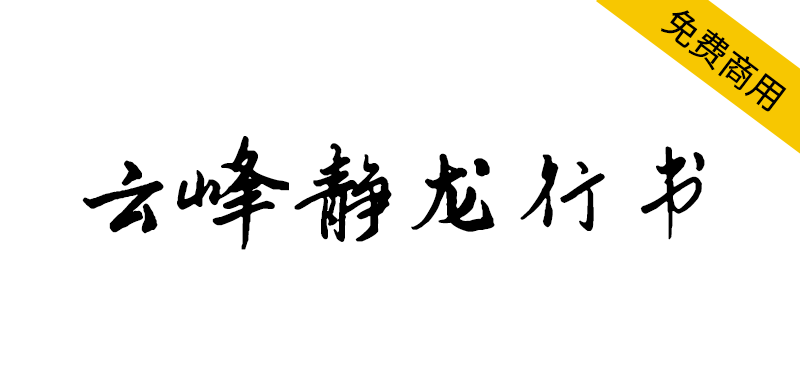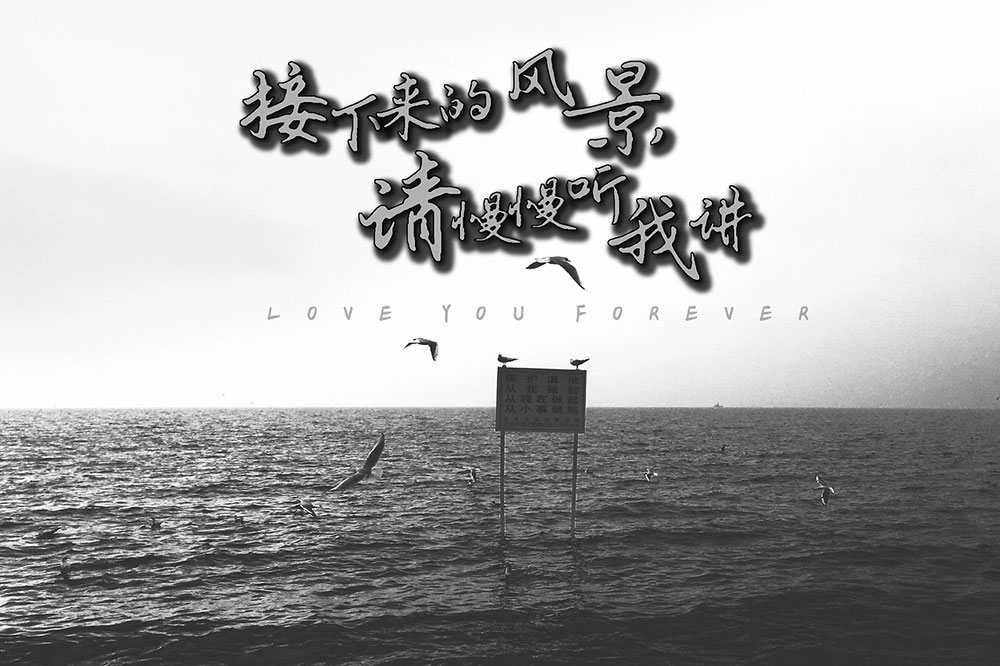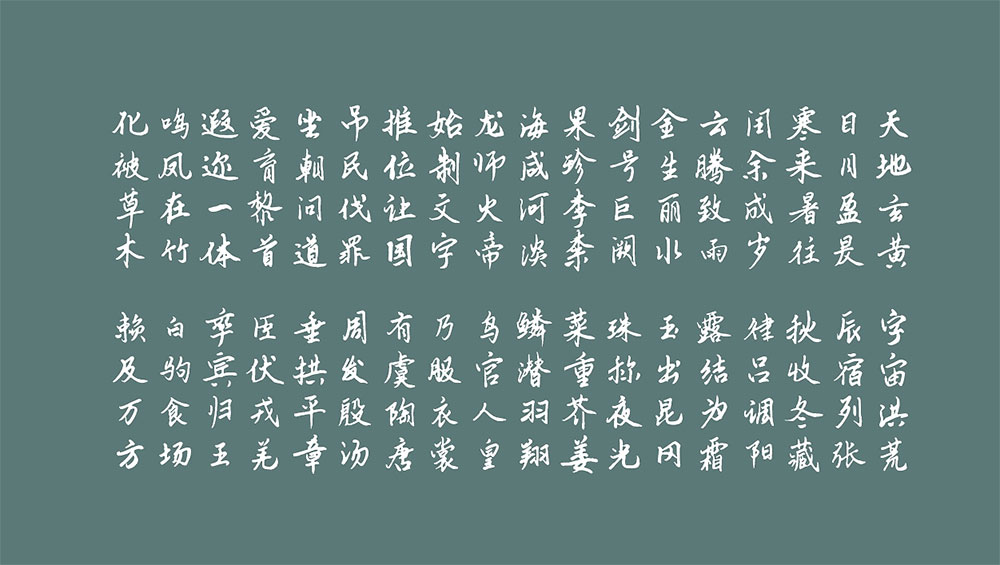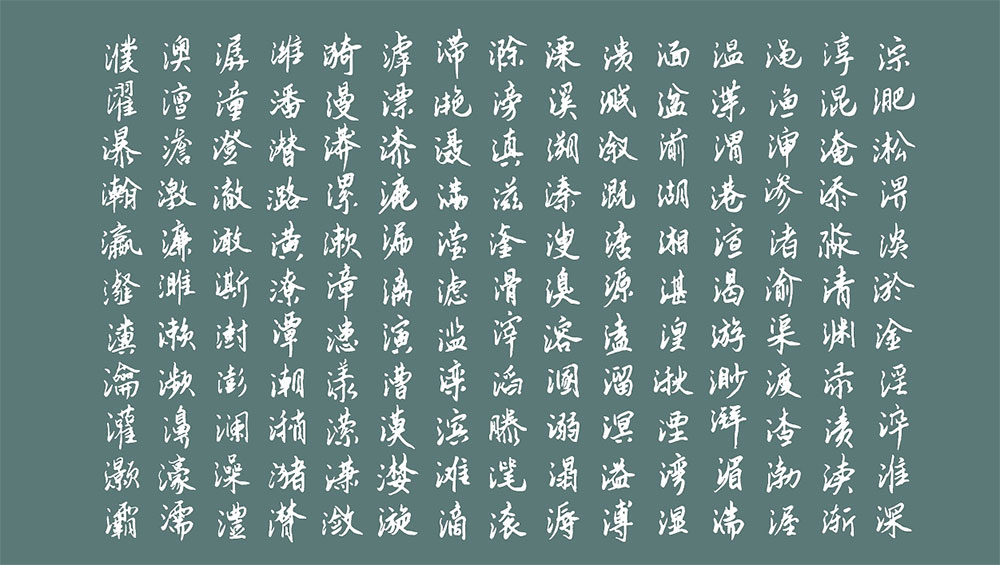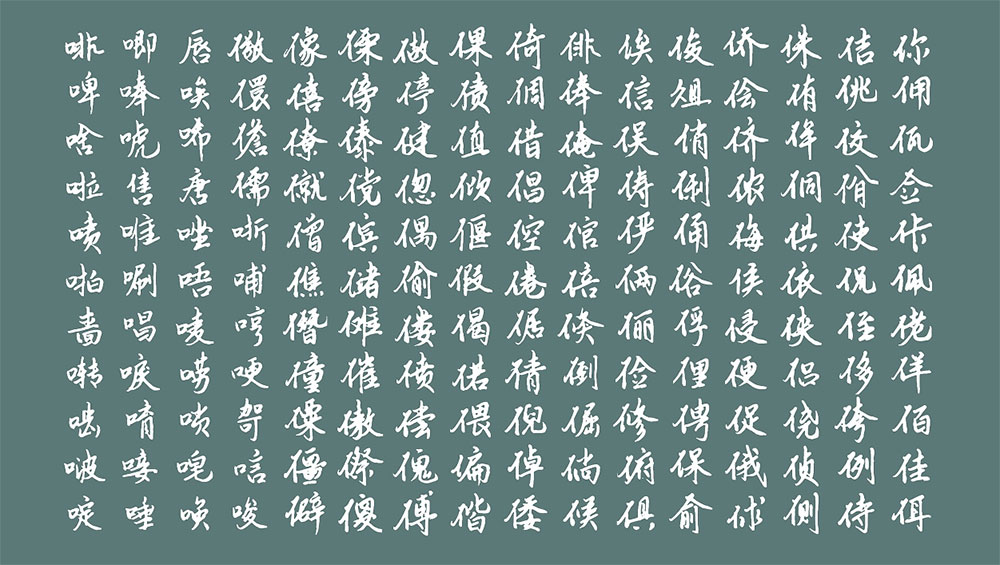
【云峰静龙行书】云峰字库首款免费商用字体,行书风格
云峰静龙行书是云峰字库首款免费商用字体,字体特点是端正平稳,放纵流动。字体以欤侧代替平整,比较复杂的笔画变的更加的简单省略,点画之间的呼应是用勾、挑、牵丝来进行加强的,用圆转的笔画代替了方折的笔画。禁止二次修改字体、禁止销售字体。违者追究法律责任。